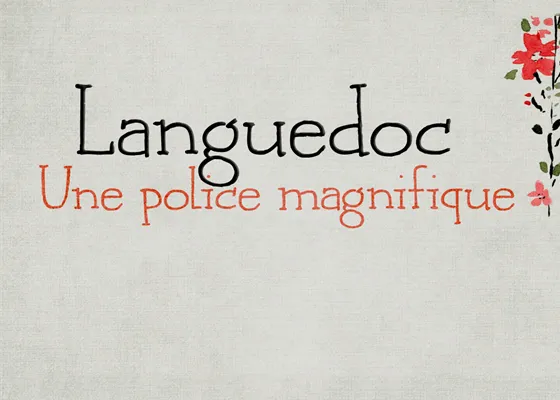
A DK Languedoc Font é uma fonte divertida e elegante ideal para projetos pessoais que valorizam a criatividade e a simplicidade. Com seu design leve e fluido, essa fonte combina perfeitamente com qualquer projeto de gráficos, desde cartazes e outdoors até designs digitais como sites e interfaces de aplicativos móveis. A DK Languedoc é particularmente adequada para uso em identidades corporativas jovens e vibrantes, ou mesmo para trabalhos que exigem uma paleta de cores alegres e versátil. Se você está procurando uma fonte com mais recursos, como os desenhos extras para jogos, apps e software, então deve considerar adquirir o pacote completo. Esta opção inclui tudo o que há em Languedoc, desde as características básicas até os detalhes adicionais e kerning precisas para garantir uma leitura confortável de texto. Em contrapartida, a versão gratuita do demo da fonte é dedicada apenas ao uso pessoal, não permitindo seu uso comercial sem um pagamento adicional. Combinar a DK Languedoc Font com o design adequado, você pode criar experiências gráficas únicas e memoráveis.